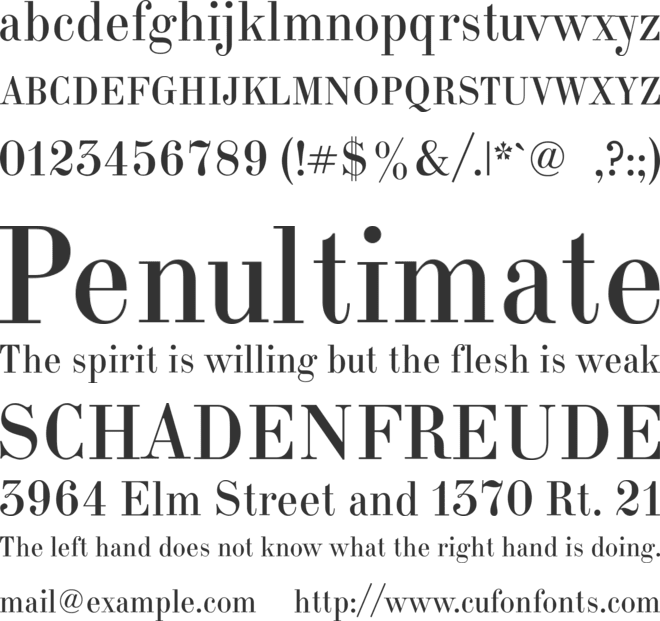
Die kurze elektronisch Version der alte «Jelisawethinskaja» Garnitur aus der Diaghilew-Zeitschrift «Mîr iskusswa», mit Ergänzungen deutscher Umlaute und des «sz» («ß»), die für ine vollwertige Förderung der deutschen Sprache notwendig sind, sowie samt eines Paars Buchstaben mit dem Makron, die für die Wiedergabe von Gräzismen mittels lateinischer Schrift notwendig sind, sowie des neu eingeführten russischen Rubelzeichens «₽».